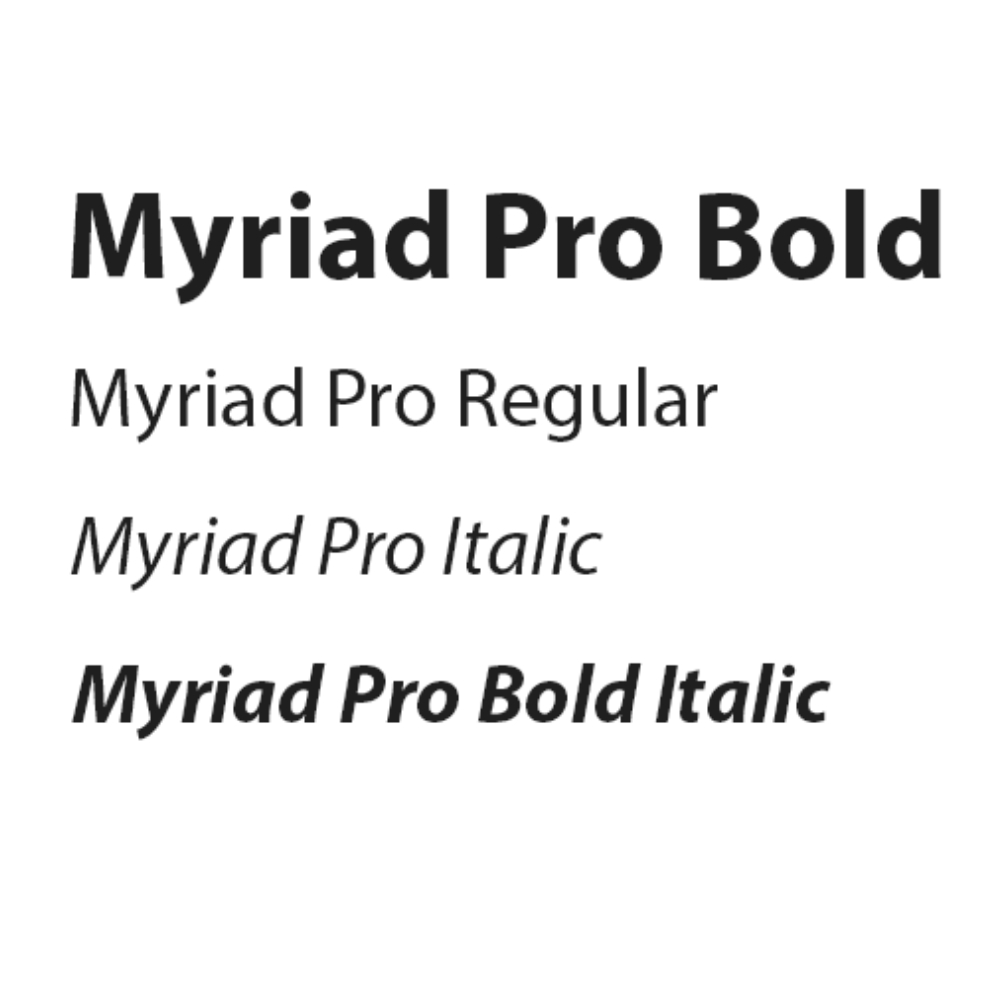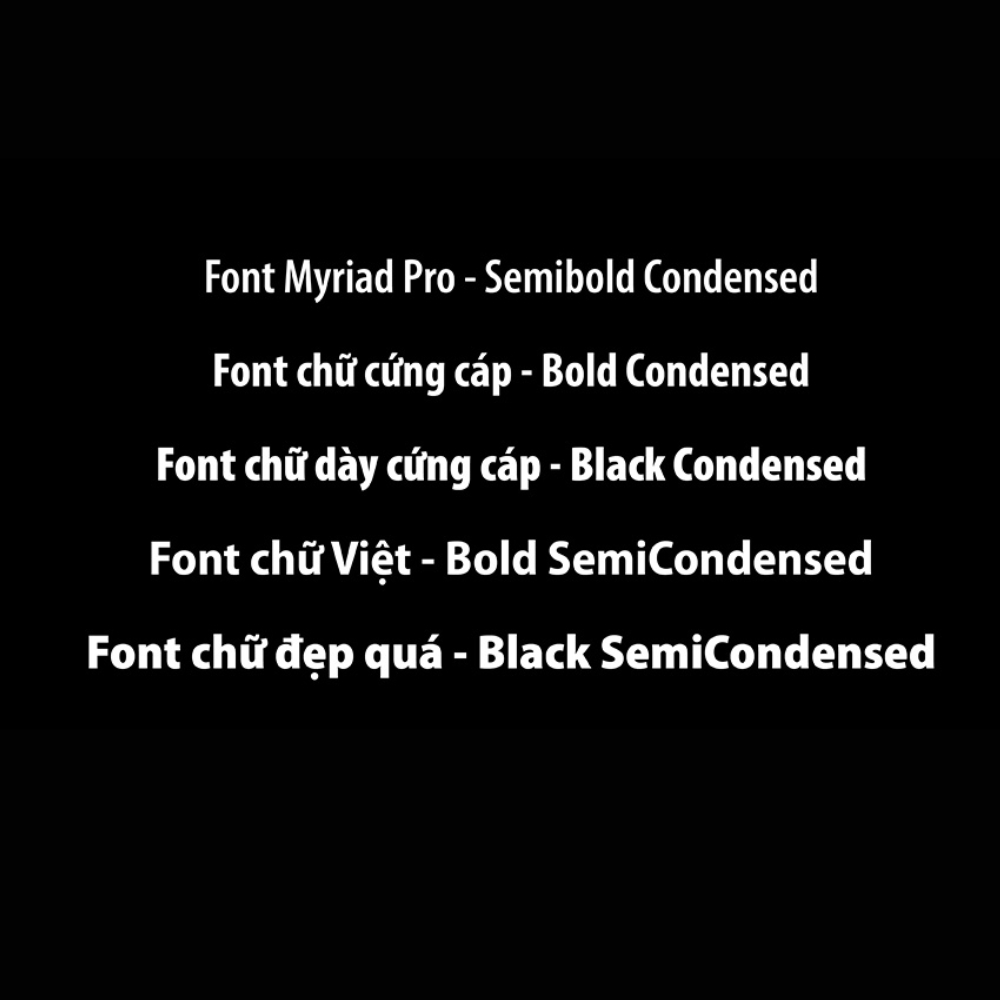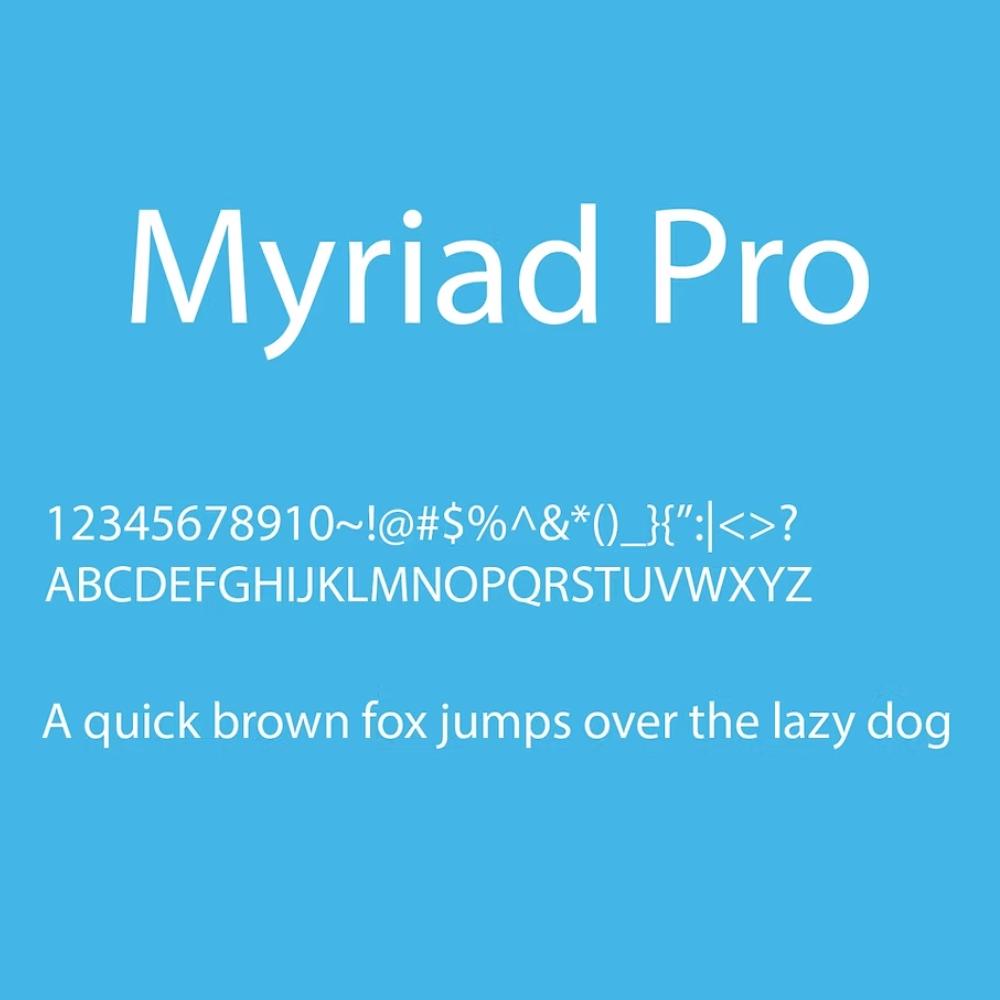
Không ít designer khi tìm link download font Myriad Pro gặp phải tình trạng tải về nhưng bản Việt hóa bị lỗi dấu, các ký tự tiếng Việt bị “nhảy” font hoặc nét chữ bị biến dạng khi in ấn khổ lớn.
Thấu hiểu điều này, In Viva cung cấp bộ link tải font Myriad Pro Việt hóa đầy đủ các định dạng từ Regular, Italic đến Bold chuẩn thiết kế, giúp bạn hoàn thiện các ấn phẩm bao bì, túi giấy và quà tặng doanh nghiệp một cách chuyên nghiệp nhất.
Dưới đây là link tải bộ font Myriad Pro đã được kiểm tra kỹ lưỡng về độ hiển thị, tương thích tốt với các phần mềm thiết kế chuyên dụng như Adobe Illustrator, Photoshop, CorelDRAW và các phần mềm văn phòng. Bộ font này bao gồm đầy đủ các biến thể từ nét mảnh đến nét đậm, hỗ trợ tốt cho cả nội dung văn bản và tiêu đề.
- Myriad Pro Regular: Dùng cho nội dung văn bản dài, hồ sơ năng lực.
- Myriad Pro Bold: Dùng cho tiêu đề, làm nổi bật thông tin quan trọng.
- Myriad Pro Italic: Dùng cho các ghi chú hoặc trích dẫn sáng tạo.
- Myriad Pro Condensed: Tiết kiệm diện tích cho các thiết kế nhỏ như thân bút, nhãn tem.
Ưu điểm khi sử dụng Myriad Pro Việt hóa trong in ấn quà tặng, bao bì giấy
Trong lĩnh vực sản xuất bao bì và quà tặng doanh nghiệp, việc lựa chọn font chữ không chỉ dừng lại ở yếu tố đẹp mắt mà còn phải đảm bảo tính kỹ thuật. Myriad Pro sở hữu những đặc điểm “vàng” khiến nó trở thành lựa chọn hàng đầu tại Xưởng In Viva.
Độ hiển thị sắc nét trên mọi chất liệu
Myriad Pro thuộc nhóm Humanist Sans-serif với các đường nét được tính toán kỹ lưỡng về tỷ lệ. Khi tải font Myriad Pro Việt hóa để thiết kế in ấn, các nét chữ không quá mỏng cũng không quá dày, giúp quá trình in lụa trên túi vải hay in UV trên bình giữ nhiệt luôn sắc nét. Ngay cả khi thu nhỏ font xuống kích thước 6pt để in thông tin phụ trên hộp mỹ phẩm, chữ vẫn không bị nhòe hay mất nét.
Tính tương thích cao với bảng mã Unicode
Lỗi lớn nhất của các designer tại Việt Nam là dùng font không hỗ trợ tiếng Việt hoàn chỉnh, dẫn đến các dấu (huyền, sắc, hỏi, ngã, nặng) bị lệch vị trí hoặc biến thành ký tự lạ. Bộ font Myriad Pro Việt hóa chuẩn mà In Viva cung cấp đã xử lý triệt để vấn đề này, đảm bảo các ký tự như “đ”, “ư”, “ơ” đồng nhất về độ dày và khoảng cách với các chữ cái khác.
Phong cách trung tính, phù hợp đa dạng ngành nghề
Myriad Pro không quá cứng nhắc như Arial nhưng cũng không quá cổ điển như Times New Roman. Nó mang vẻ đẹp hiện đại, chuyên nghiệp, phù hợp để in logo lên quà tặng cho các ngân hàng lớn như Vietcombank, BIDV hay các tập đoàn công nghệ như FPT, Viettel. Sự đa dạng trong các biến thể (Bold, Semibold, Light) cho phép designer tạo ra sự phân cấp thông tin rõ ràng trên bao bì hộp giấy cao cấp.
| Ứng dụng thực tế | Phiên bản đề xuất | Ưu điểm kỹ thuật |
|---|---|---|
| In túi giấy, hộp quà tặng | Myriad Pro Semibold | Tạo điểm nhấn, sang trọng, dễ đọc từ xa. |
| Khắc laser bình giữ nhiệt, bút ký | Myriad Pro Bold | Nét chữ đậm giúp tia laser đi chuẩn, không bị đứt quãng. |
| In tem nhãn, hướng dẫn sử dụng | Myriad Pro Condensed | Tối ưu không gian, chứa được nhiều chữ trên diện tích nhỏ. |
| Danh thiếp, hồ sơ doanh nghiệp | Myriad Pro Regular | Trang nhã, tạo cảm giác tin cậy cho người đọc. |
05 lỗi thường gặp khi sử dụng font Myriad Pro trong thiết kế
Mặc dù là bộ font tối ưu, nhưng nếu người dùng không chú ý đến các yếu tố kỹ thuật, sản phẩm cuối cùng vẫn có thể gặp sự cố. Dưới đây là những lỗi phổ biến mà khách hàng của In Viva thường gặp phải trước khi được đội ngũ kỹ thuật hỗ trợ:
- Lỗi Missing Font (Thiếu font): Đây là lỗi kinh điển khi bạn thiết kế ở máy mình nhưng khi gửi file sang máy khác hoặc gửi đến xưởng in, máy đó không có sẵn font Myriad Pro. Hệ thống sẽ tự động thay thế bằng một font mặc định khiến bố cục bị xô lệch hoàn toàn.
- Sử dụng bản download font myriad pro bold không chính thức: Nhiều trang web cung cấp bản “fake bold” (tự làm đậm bằng phần mềm thay vì dùng file Bold gốc). Điều này khiến nét chữ bị thô, các khe hở trong chữ (như chữ o, e) bị lấp kín khi in ấn.
- Sai hệ màu khi thiết kế văn bản: Designer thường để chữ màu đen ở hệ màu RGB hoặc đen 4 màu (C:100 M:100 Y:100 K:100). Khi in trên hộp giấy, chữ Myriad Pro vốn thanh mảnh sẽ bị chồng màu không khít, gây ra hiện tượng chữ bị bóng ma hoặc lem màu.
- Khoảng cách chữ (Kerning) quá hẹp: Khi thiết kế trên màn hình độ phân giải cao, bạn thấy chữ rất rõ. Tuy nhiên, nếu in trên chất liệu giấy kraft có độ thấm mực cao, mực sẽ lan ra (dot gain). Nếu không nới rộng khoảng cách chữ, các ký tự sẽ dính vào nhau rất khó đọc.
- Lỗi mã hóa bảng mã: Một số phiên bản cũ vẫn dùng bảng mã VNI hoặc TCVN3 thay vì Unicode. Điều này khiến việc tìm kiếm và chỉnh sửa nội dung trên các nền tảng hiện đại gặp nhiều khó khăn.